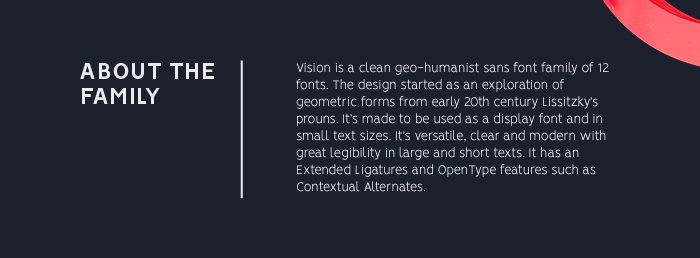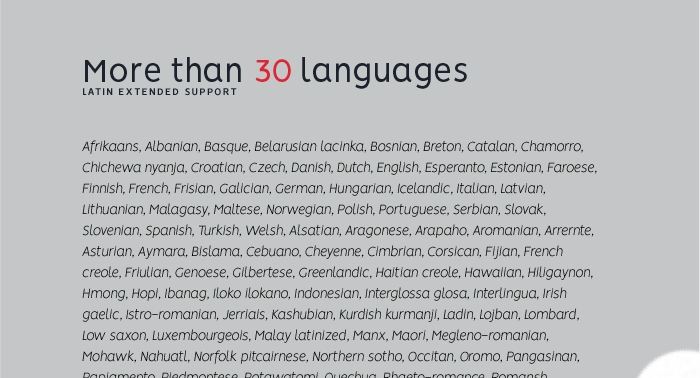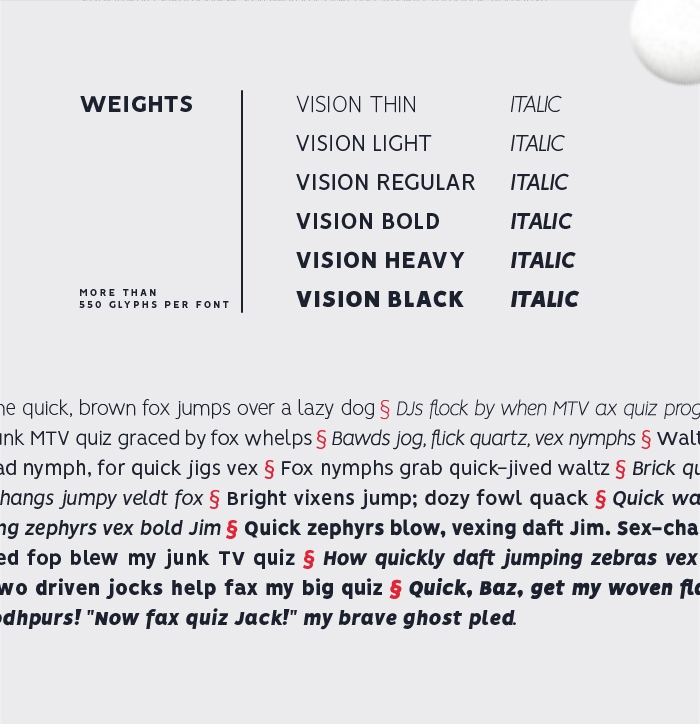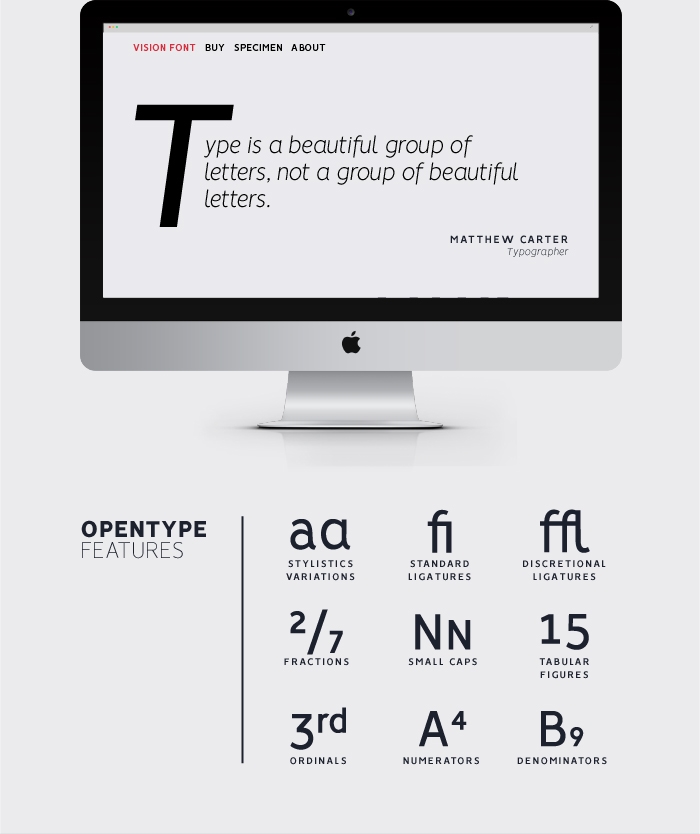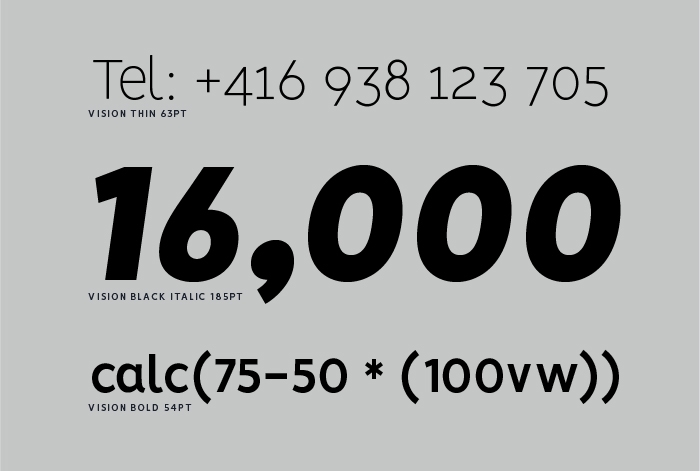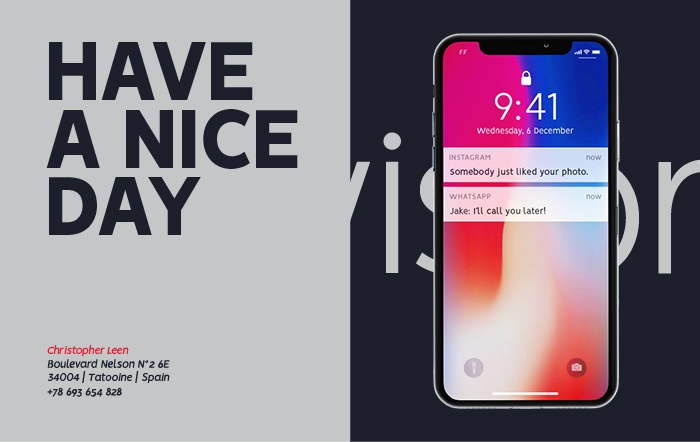
Vision is a clean, geometric sans serif with humanist touch. The type family consists of 12 fonts.
It’s design started as an exploration of geometric forms from early 20th century Lissitzky’s prouns. Perfect for display and small text, it’s born to be versatile, a clear and modern font with great legibility in large and short texts. In addition, it has extended ligatures, OpenType features and alternative glyphs which provide flexibility and uniqueness wherever it is placed